黑体作为一款经典标志性的字体,是每个设计师的必搜字体。黑体字也被称作为等线体,属于无衬线字体的一种。字架吸收了宋体字的结构有点,去掉了衬线装饰,整体风格简洁大方,极具时尚感和现代感。可以说是百搭字体,可塑性极强。可以表达出严谨的商业气息,也可以表现出清新灵动的气息。
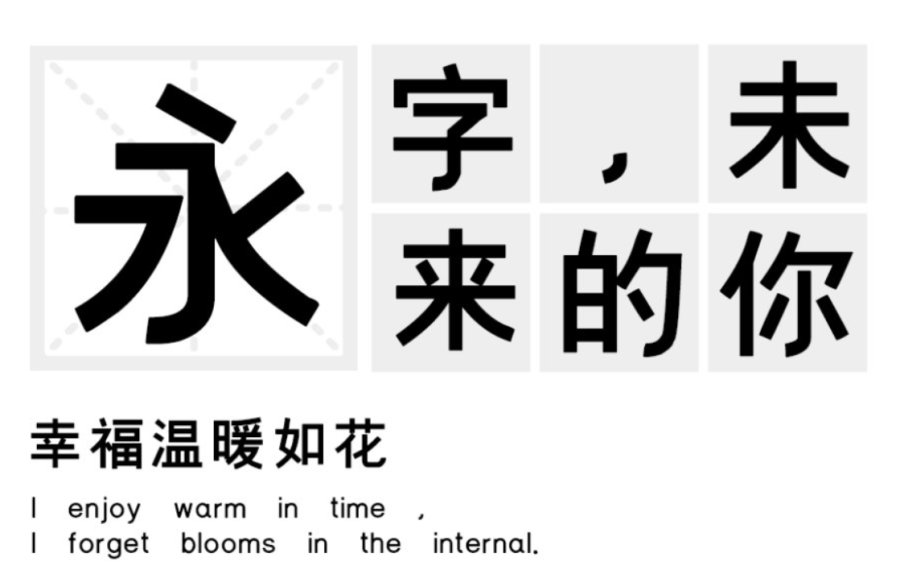
汉标粗黑体:笔画清朗有劲,简约美观。虽为等线的黑体,却具有传统中国书法的气韵,字字皆生动有神。具张力的曲线,加上精准的几何线条结构,汉标粗黑体稳重的风格应用于信息排印与显示实为上佳选择。
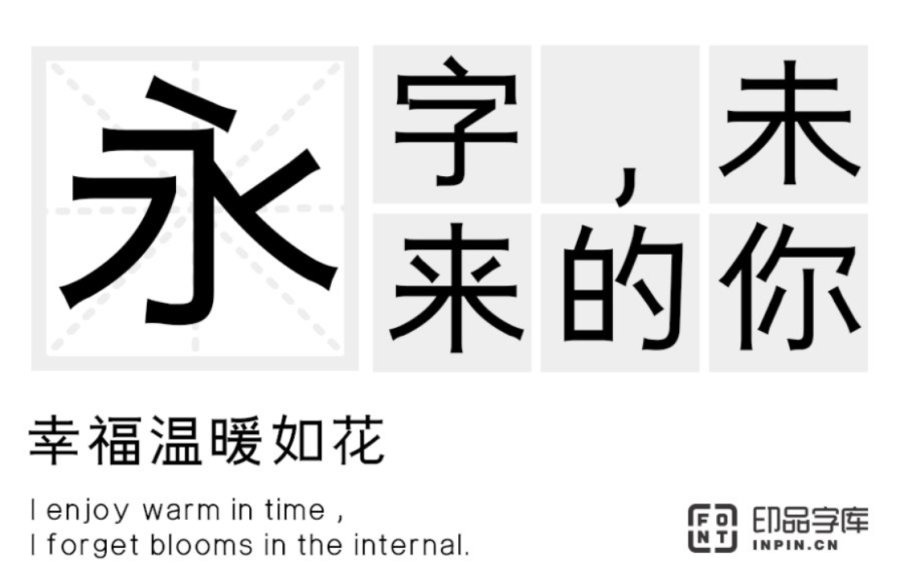
印品黑体:这款字体在传统黑体上做减法,撕掉俗套的外衣,不再追求完美比例,字形方正,简约易读。适用于游戏、logo设计、广告、印刷、标题、招牌等各类领域。
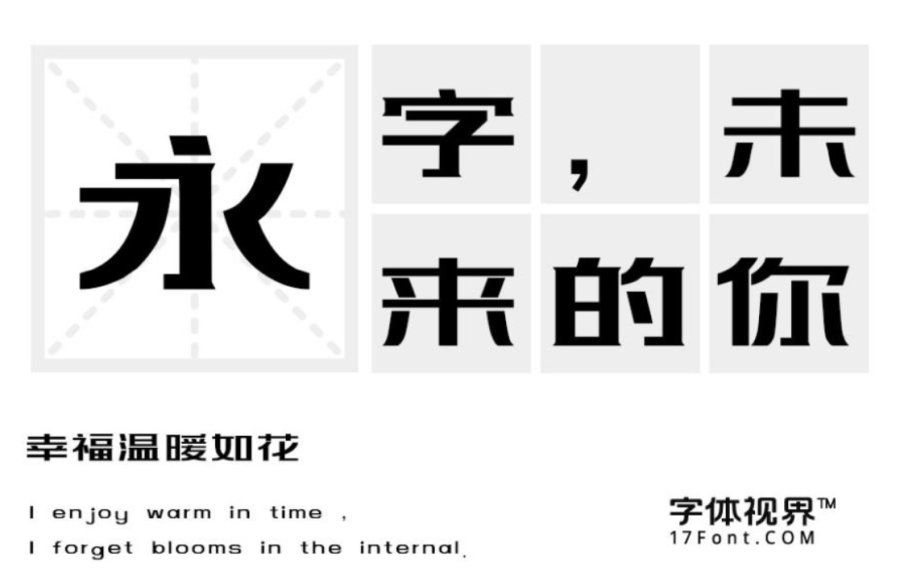
上首维黑体:这款字体风格稳重呈方块形,字体笔画竖折处细节处理,是此套字库的亮点。字库整体特征坚硬、有力,具有现代、国际化的指向性,适用于搭配标志、广告标语、商业广告等高端领域。